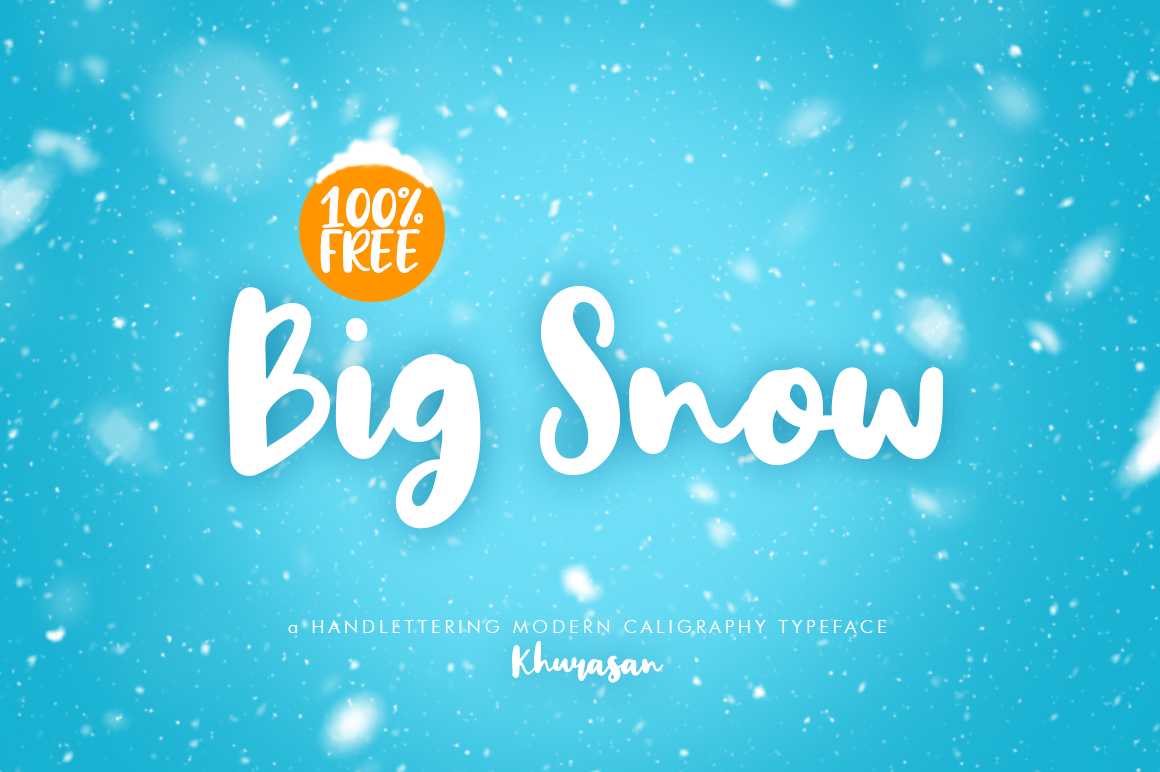
Big Snow Script Font – Download Grátis
Descubra a sofisticação do Big Snow Font neste estilo script. Especialmente projetado para personalizar sua marca ou identidade visual, este font é perfeito para criadores de design como você. Ideal tanto para assinaturas e identidades visuais quanto para materiais de evento como cartazes e editoriais, também serve como uma excelente escolha para capas de livros, embalagens, cartões de agradecimento ou mesmo em banners publicitários. Big Snow foi projetado por khurasan, oferecendo uma variedade de opções que permitem personalização perfeita. Essa font traz elegância e delicadeza à qualquer projeto, tornando-a um recurso indispensável para designers apaixonados por estilos elaborados e fluidos. Com sua disposição fluída e detalhes sutis, Big Snow é uma ótima opção para aqueles que valorizam a qualidade em seus projetos digitais.